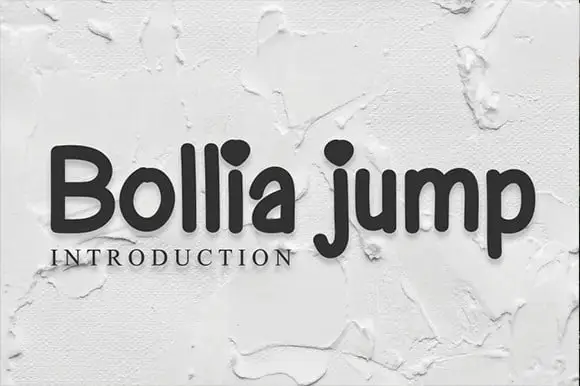
A Bollia Jump Font é uma elegante escolha para projetos que exigem estilo e sofisticação. Suas linhas sólidas e detalhes bem trabalhados tornam essa fonte perfeita para aplicações variadas, como displays de parede, convites de casamento, logotipos de mídia social, anúncios, embalagens de produtos, designs dos produtos, etiquetas, fotografia ou até mesmo para marcar. Seu design elegante e versátil também se destaca em invições, papéis de parede, criação de estação, e qualquer projeto que exige uma escrita a mão com sabor. O designer andikastudio trouxe essa fonte para oferecer opções impecáveis ao seu próximo trabalho gráfico.